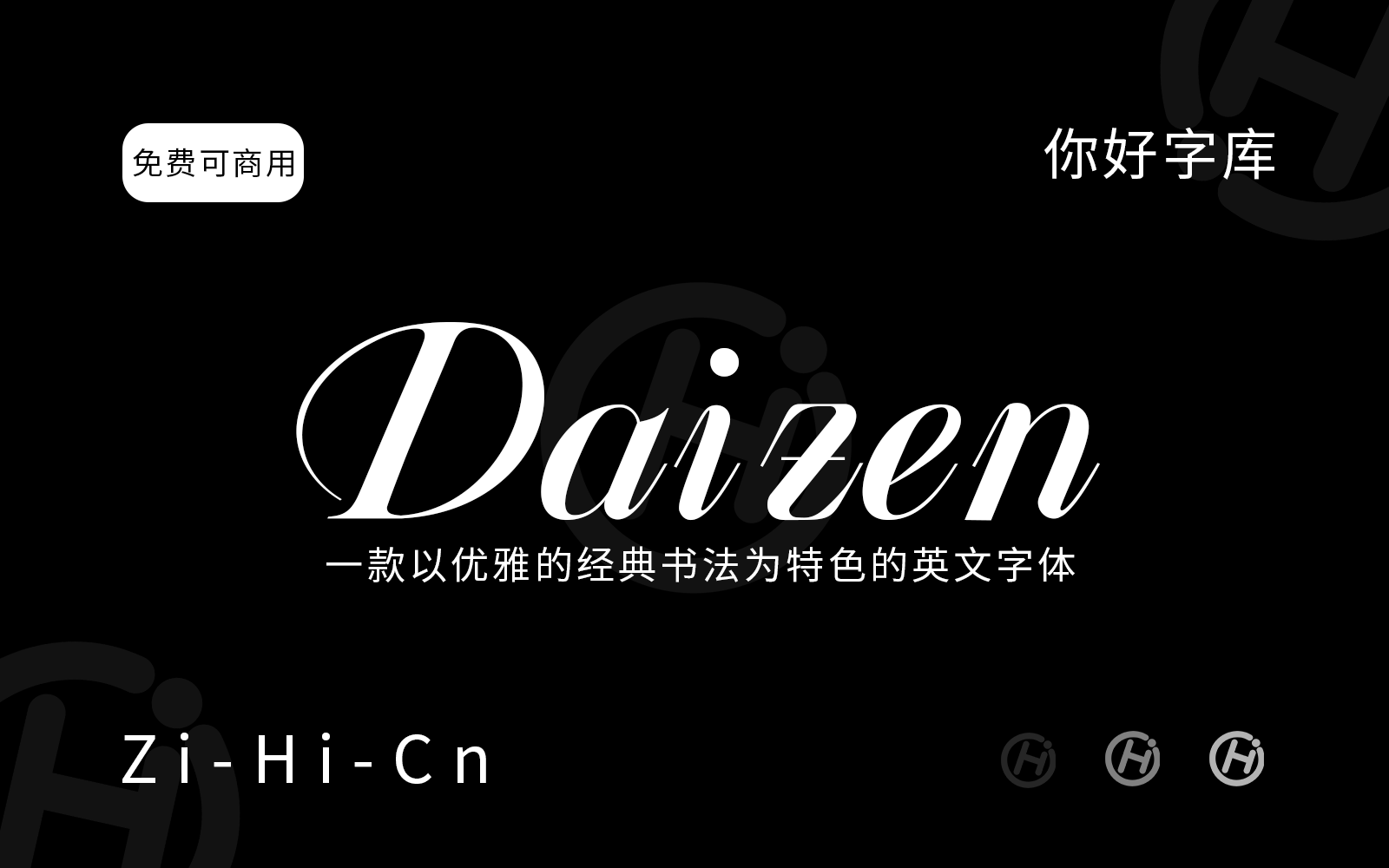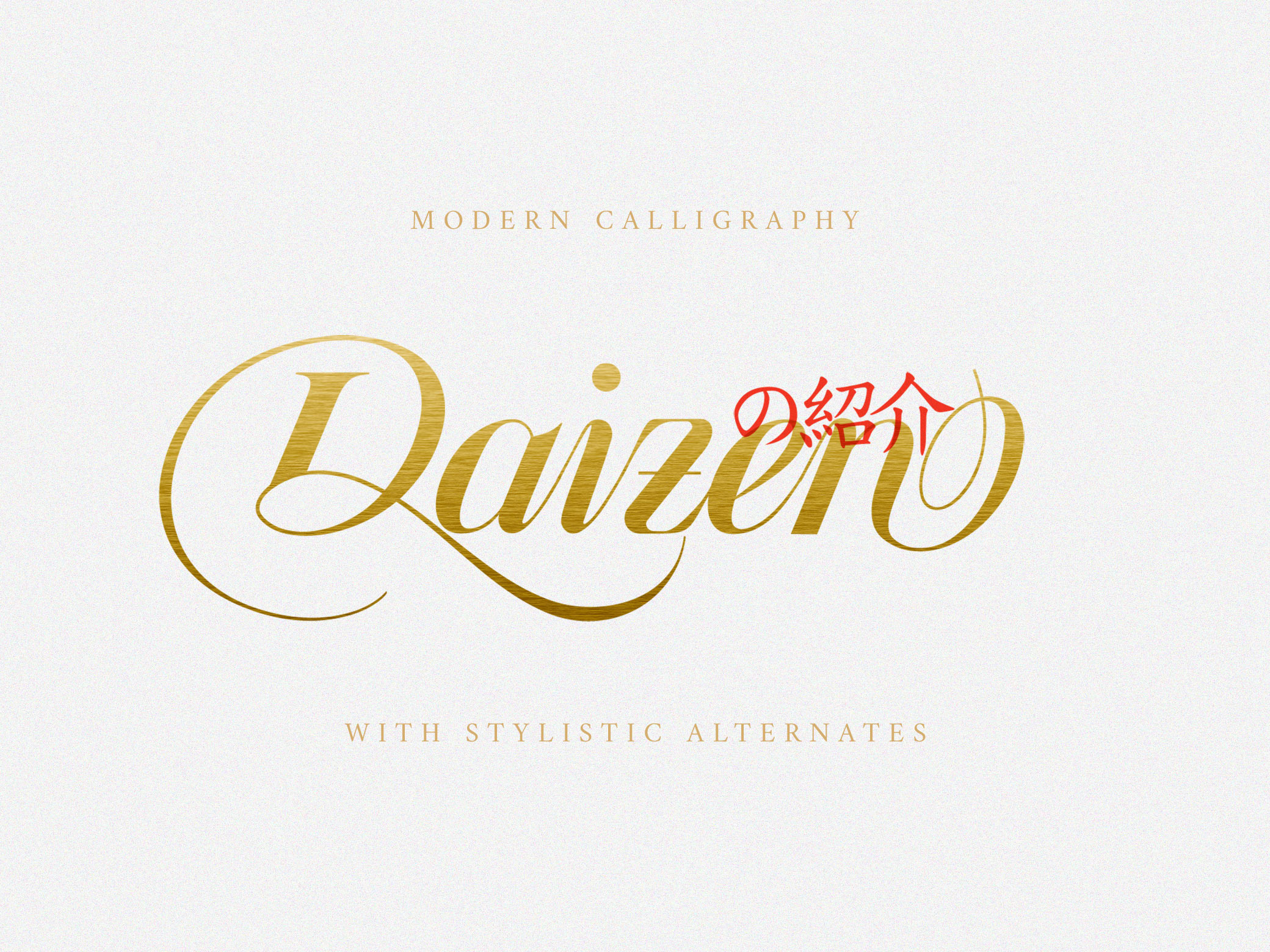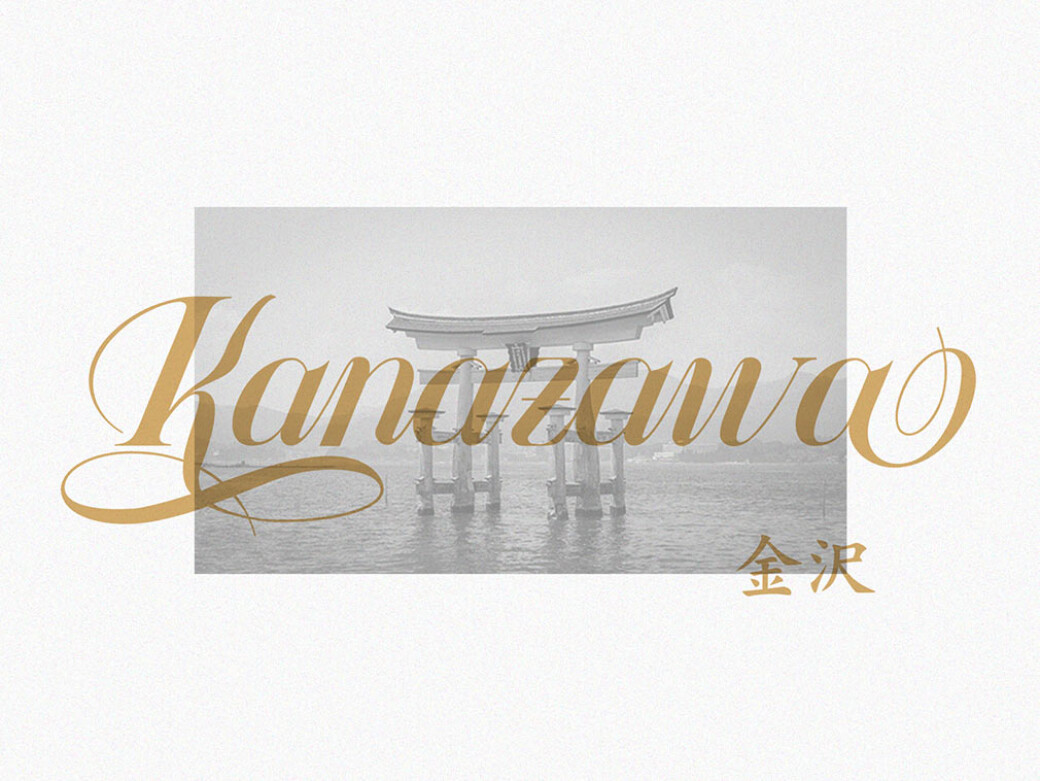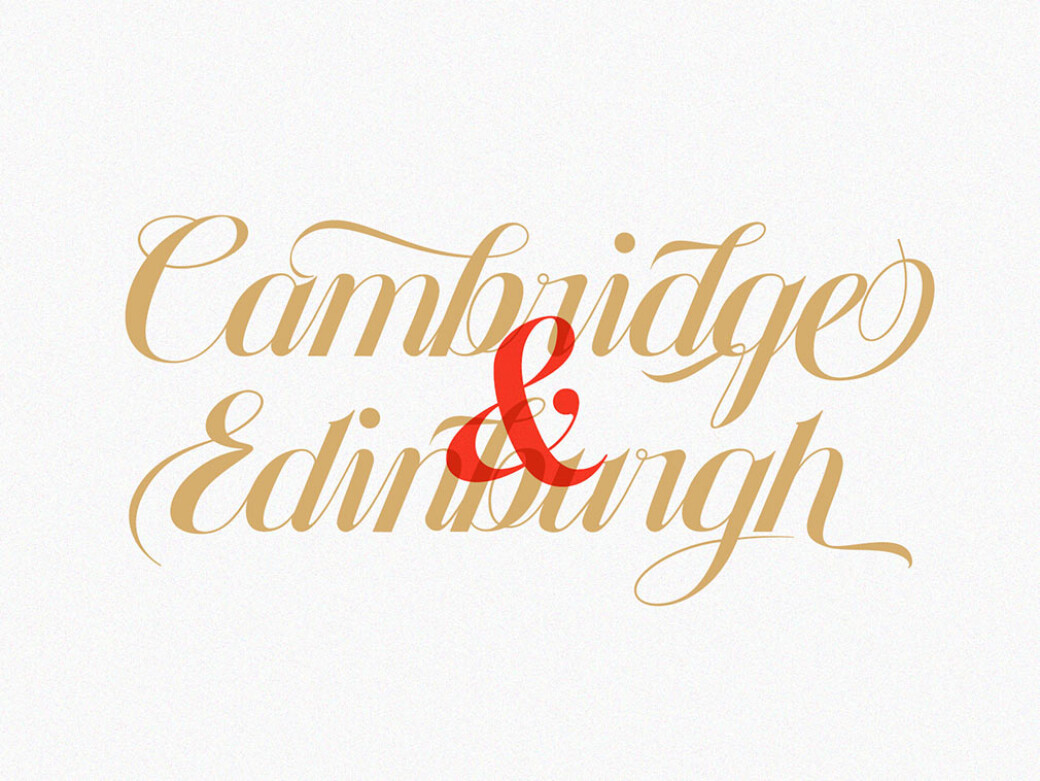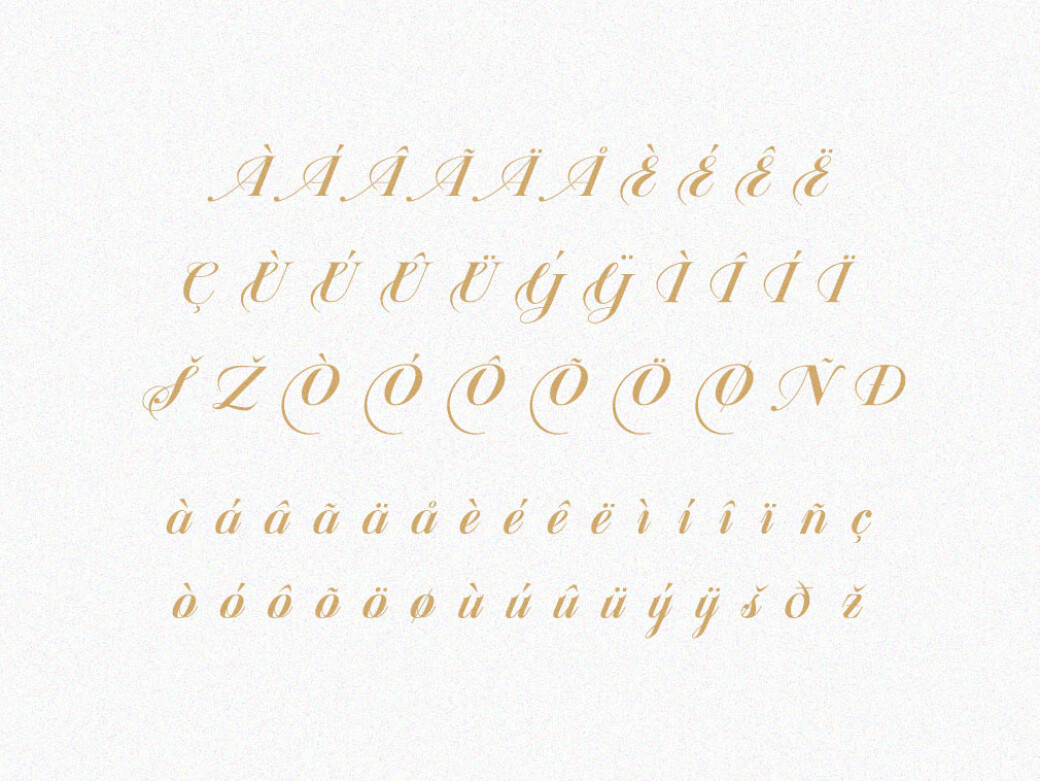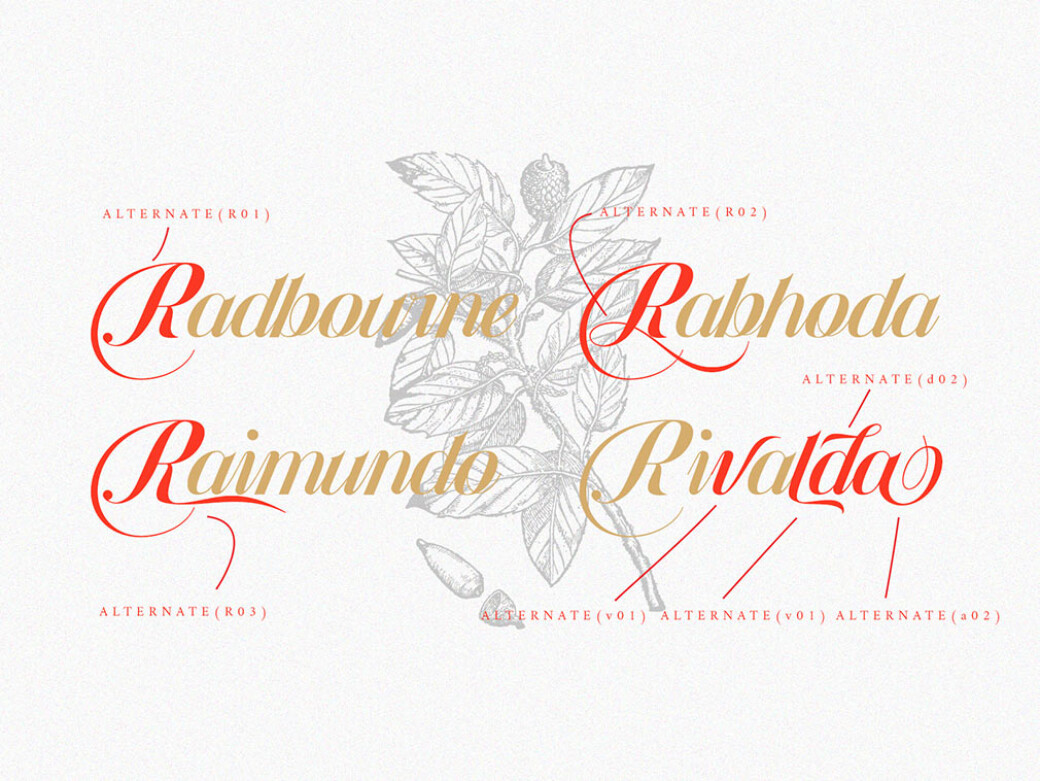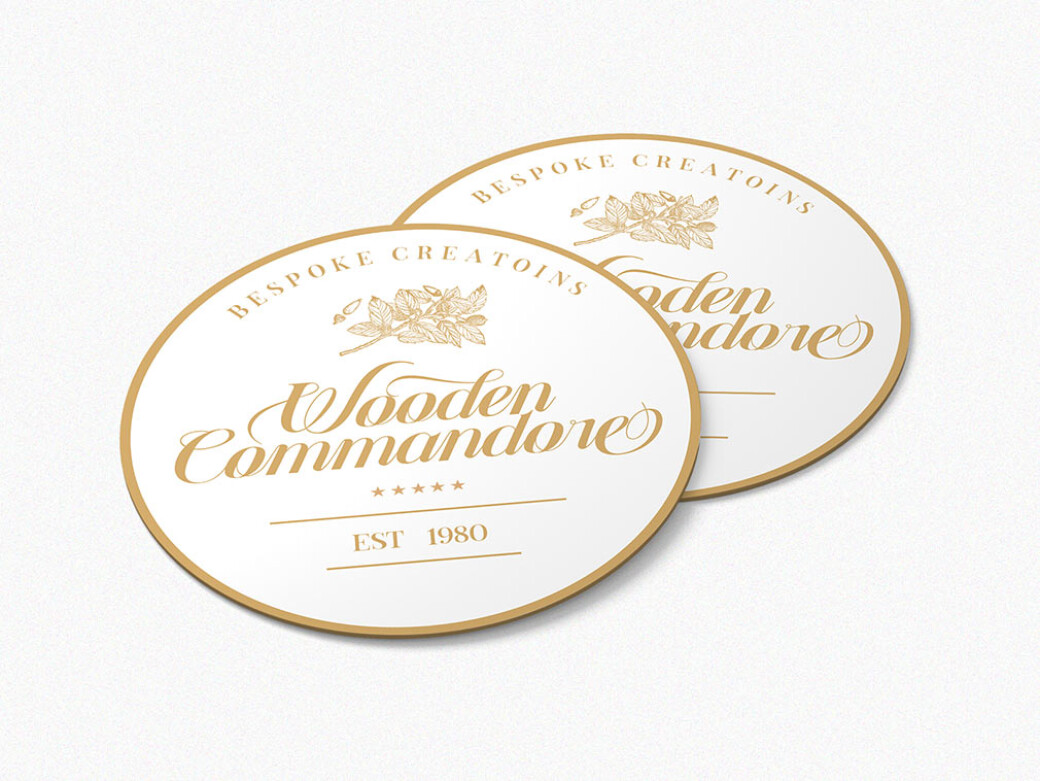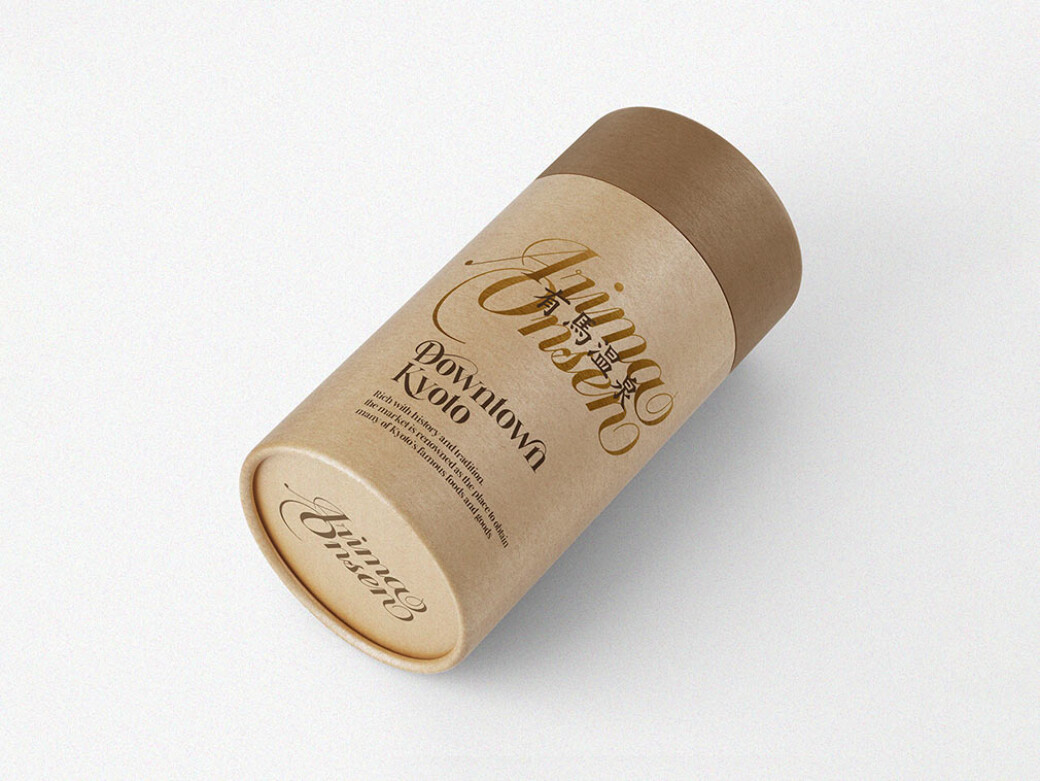
Daizen
字体简介
“Daizen”是一款由设计师 Tanzil Adduha(Damelev)创作的书法风格字体,首次发布于2020年7月。它属于手写脚本字体(Script Font),以优雅的经典书法为特色,字形流畅,上下行笔(ascenders 和 descenders)带有干净的循环曲线,大写字母形式优雅,整体散发自由灵动的气息。它的倾斜角度较低,确保了良好的可读性,同时保留了书法字体的艺术感。